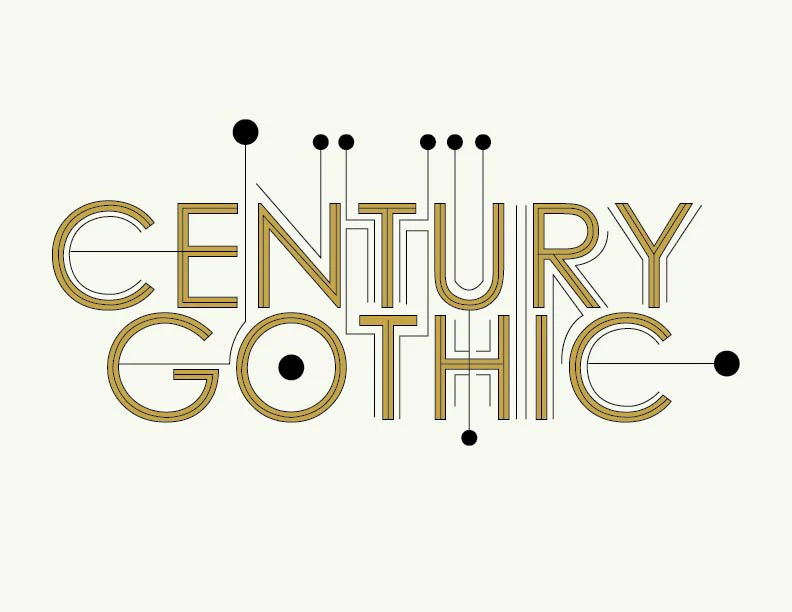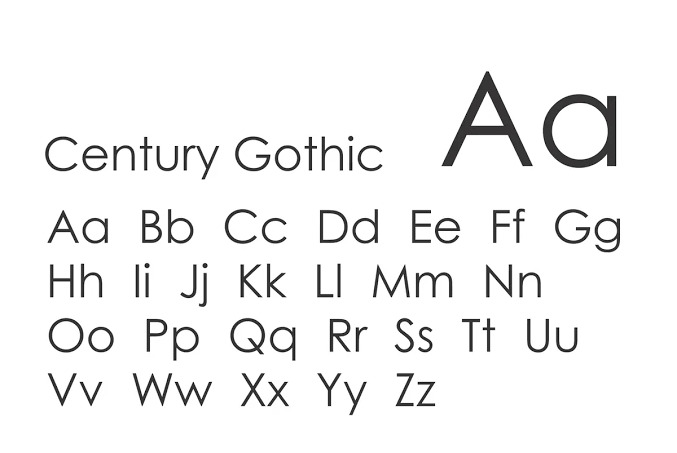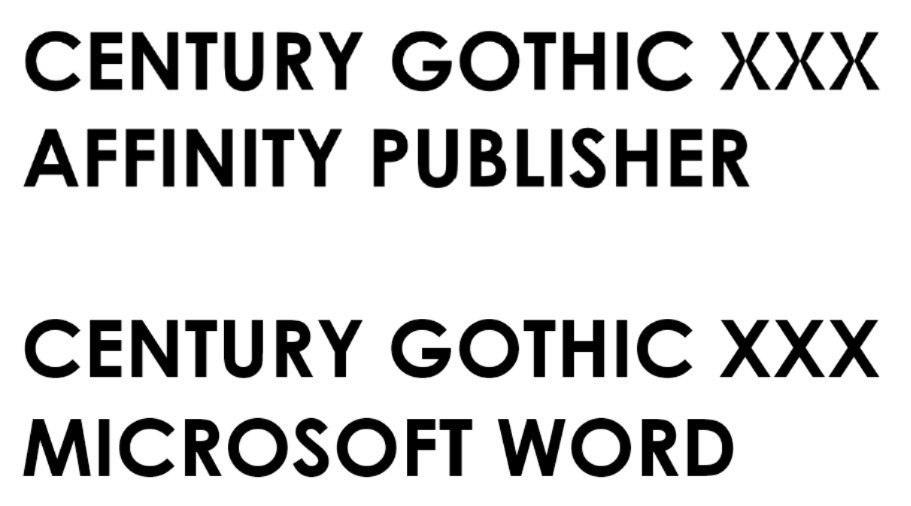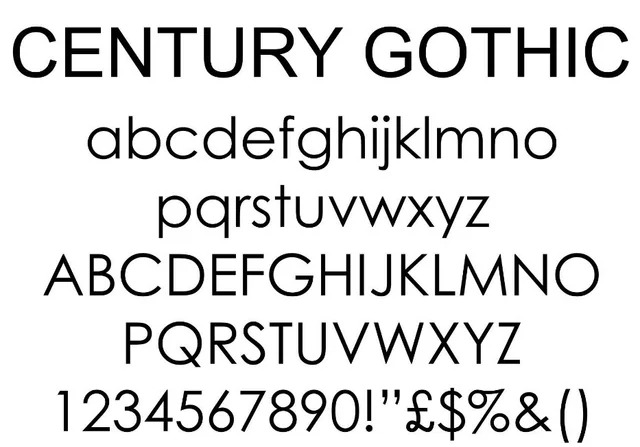
Font chữ Century Gothic Việt hóa là bộ phông chữ thuộc dòng Geometric Sans-serif kinh điển lấy cảm hứng từ phong trào thiết kế hình học Bauhaus thập niên 1930, nổi bật với các đường tròn, chiều cao ký tự lớn và độ dày nét thanh thoát. Sở hữu vẻ ngoài hiện đại, phóng khoáng và đậm chất công nghệ, kiểu chữ này giúp các kiến trúc sư, nhà thiết kế kiến tạo diện mạo tinh tế cho các bản vẽ phối cảnh văn phòng container, hồ sơ ý tưởng kiến trúc hay hệ thống biển chỉ dẫn nhà lắp ghép thông minh.
Đường cong tròn đẹp và tính tiết kiệm mực in của font chữ Century Gothic Việt hóa
Điểm cuốn hút của font chữ Century Gothic Việt hóa nằm ở tỷ lệ hình học tròn xoe ở các ký tự như ‘o’, ‘c’, ‘d’, ‘b’, tạo nên một nhịp điệu thị giác mở rộng và cực kỳ thông thoáng. Độ dày nét được duy trì đồng đều xuyên suốt, loại bỏ các chi tiết thừa thãi để hướng tới sự minh bạch và tính thực dụng cao trong in ấn hồ sơ. Phiên bản Việt hóa do BCD House tuyển chọn đã được xử lý bảng mã Unicode chuẩn xác, giúp các dấu thanh tiếng Việt nương theo các đường vát tròn mà không làm biến dạng cấu trúc thanh mảnh của bộ gốc.
Sự ổn định về mặt thị giác của dòng font này giúp văn bản toát lên vẻ văn minh, tối giản và tư duy khoa học. Một ưu điểm thú vị là các đường nét thanh mảnh của Century Gothic giúp tiết kiệm đáng kể lượng mực in khi xuất bản các tập tài liệu dày hàng trăm trang so với các phông chữ Sans-serif thông thường.
| Phân loại phong cách | Geometric Sans-serif / Modernist / Ink-saving |
| Các dòng tương đồng | Century Gothic, All Round Gothic Việt hóa, Futura |
| Mục đích phù hợp | Hồ sơ bản vẽ CAD, biển tên văn phòng, website |
Tư vấn từ chuyên viên: Century Gothic sở hữu chiều ngang chữ rất rộng. Để bản thiết kế đạt hiệu quả thẩm mỹ tốt, bạn nên sử dụng biến thể Bold cho các tiêu đề chính hoặc tên dự án. Phần nội dung mô tả kỹ thuật chi tiết nên dùng kiểu Regular ở kích thước 10-11pt để tận dụng tối đa tính thông thoáng và dễ đọc của bộ chữ.
03 Ứng dụng phông chữ Century Gothic vào công trình thực tế
Nhờ diện mạo khoa học và tính đa năng cao, bộ phông chữ này mang lại giá trị thực tế lớn trong khâu quản lý và quảng bá các dự án xây dựng hiện đại:
- Hệ thống biển chỉ dẫn cho Văn phòng Container và Showroom: Những nét chữ tròn trịa của Century Gothic rất ăn ý khi gia công chữ nổi bằng mica trong suốt dán kính hoặc alu màu trắng, giúp không gian làm việc toát lên vẻ ngăn nắp và hiện đại.
- Ghi chú thông số kỹ thuật trên bản vẽ AutoCAD: Độ rõ nét của Century Gothic hỗ trợ đắc lực cho kỹ sư khi trình bày các thông số về vật liệu panel, kết cấu dầm thép, giúp đội ngũ giám sát thi công tại hiện trường tra cứu thông tin nhanh chóng.
- Bìa hồ sơ ý tưởng kiến trúc phong cách Bắc Âu: Sử dụng font chữ Century Gothic Việt hóa free cho tên dự án giúp tập hồ sơ toát lên vẻ ngoài tinh tế, tạo niềm tin lớn với các chủ đầu tư yêu chuộng lối sống tối giản.
03 Lưu ý bố cục font chữ Century Gothic luôn thoáng đạt và bắt mắt
Để khai thác hiệu quả vẻ đẹp của dòng font hình học tròn xoe này mà không làm tốn quá nhiều diện tích trang giấy, người thiết kế nên lưu tâm một số kinh nghiệm sau:
- Kiểm soát khoảng cách dòng: Với cấu trúc ký tự có tỷ lệ nở rộng bề ngang, bạn nên thiết lập khoảng cách dòng ở mức vừa vặn (khoảng 1.3 – 1.4 lần cỡ chữ) để các dòng văn bản giữ được sự liên kết nhịp nhàng, tránh cảm giác chữ bị dàn trải quá mức.
- Tham khảo dòng phông All Round Gothic: Nếu dự án cần nét chữ tròn đậm đà và có phần cổ điển hơn, bạn có thể kết hợp cùng all round gothic việt hóa cho các tiêu đề phụ để tạo sự đa dạng về cấp bậc thị giác.
- Lựa chọn gam màu đơn sắc dứt khoát: Century Gothic phát huy hiệu quả thị giác cao khi phối cùng các tông màu mang sắc thái hiện đại như đen than, xám khói, trắng ngọc trai hoặc xanh mint trên nền tường phẳng, làm nổi bật đường nét hình học của bộ chữ.